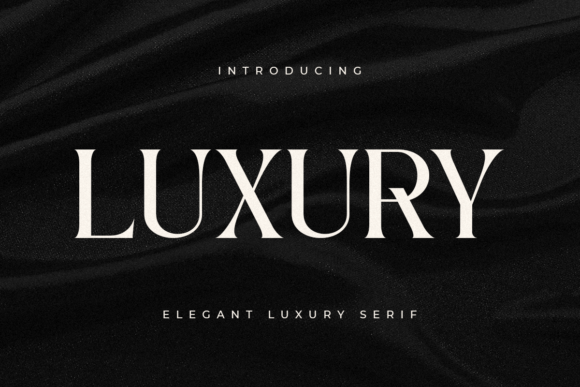
Luxury
Présentation du Luxury Font : Une Élégance Intemporelle pour Vos Projets de Design
Si vous cherchez une police de caractères qui allie sophistication et polyvalence, le Luxury Font est une option incontournable. Cette police en serif, raffinée et élégante, se distingue par son équilibre subtil entre finesse et force. Conçue pour sublimer vos créations, qu’il s’agisse de logos, de cartes de visite ou de projets éditoriaux, Luxury incarne l’essence du luxe à travers ses traits soigneusement dosés.
Caractéristiques Clés du Luxury Font
- Équilibre et variété : Ni trop fin ni trop épais, Luxury offre une harmonie parfaite entre les lettres, idéal pour une lisibilité optimale.
- Design intemporel : Son style classique et raffiné se marie à la fois avec des projets modernes et des créations vintage.
- Polyvalence : Adaptée à divers supports, de la typographie web à l’impression haut de gamme.
- Exclusivité : Une police qui évoque le luxe sans être ostentatoire, parfaite pour des marques haut de gamme.
Pourquoi Choisir le Luxury Font ?
Que vous soyez designer graphique, entrepreneur ou créateur de contenu, le Luxury Font saura transformer vos idées en œuvres d’art. Son esthétique raffinée et son caractère élégant lui confèrent une personnalité unique, capable de captiver immédiatement votre audience. Que ce soit pour un logo de marque de luxe, un catalogue de mode ou une mise en page de magazine, cette police apporte une touche de distinction qui ne laisse personne indifférent.
Applications Recommandées
Le Luxury Font excelle dans les contextes où la précision et le raffinement sont essentiels. Utilisez-le pour :
- Les identités visuelles de marques premium.
- Les projets éditoriaux (livres, magazines, affiches).
- Les designs web nécessitant une touche de sophistication.
- Les cartes de visite ou invitations élégantes.
Conclusion : Un Choix de Luxe pour un Impact Durable
Avec le Lux